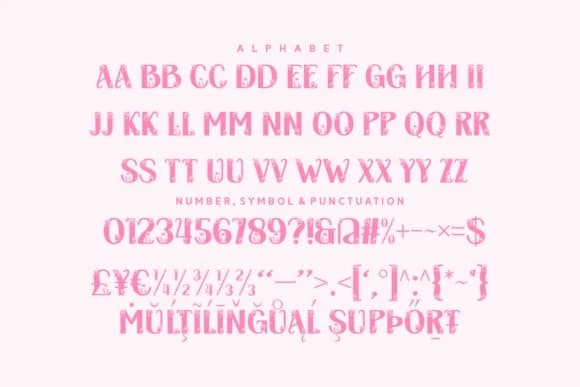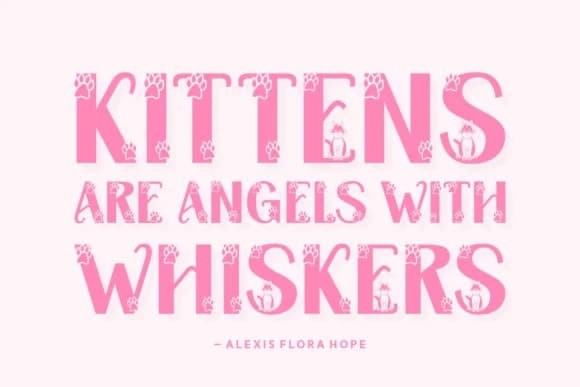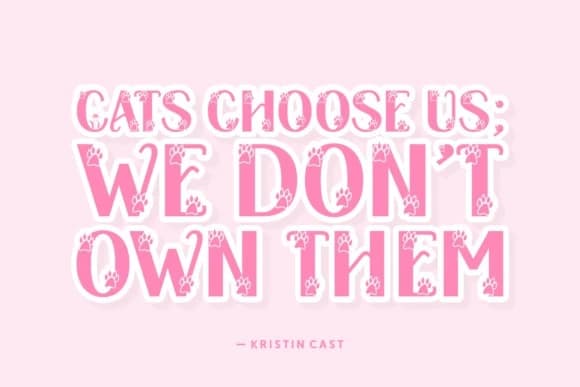
Meowy Kitties Font, dekoratif bir yazı tipidir ve oyunbaz bir ruh ile masalsı bir eğlence hissi içerir. “Meowy Kitties”i, sosyal medya paylaşımlarını ön plana çıkarmak ve fotoğraf projelerinize bir çekicilik katmak için ideal bir seçenek olarak keşfedeceksiniz.
Meowy Kitties Font, oyuncu bir ruhu ve hayal gücünün getirdiği eğlence hissini kapsayan dekoratif bir yazı tipidir. “Meowy Kitties”i, sosyal medya paylaşımlarını öne çıkarmak ve fotoğraf projelerinize bir çekicilik katmak için ideal bir seçim olarak keşfedeceksiniz.